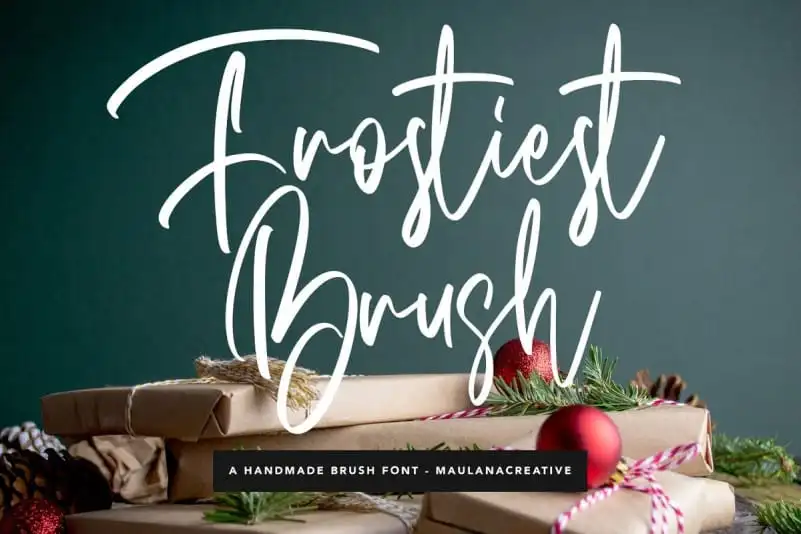
Frostiest Script Font – Download Grátis
Introduzimos a Frostiest Script Font. Esta tipografia cuidadosamente elaborada com estilos de pincelagem destaca-se pela elegância que oferece para uma variedade de projetos e promoções. Perfeitamente adaptada para assinaturas, materiais de correspondência, logotipos, citações tipográficas, capas de revistas ou livros, cabeçalhos de sites, roupas, marca e embalagens. Seja qual for o seu projeto, a Frostiest Script Font certamente será uma escolha agradável para elevar seus trabalhos ao próximo nível. Descubra agora como essa font pode potencializar suas ideias criativas.